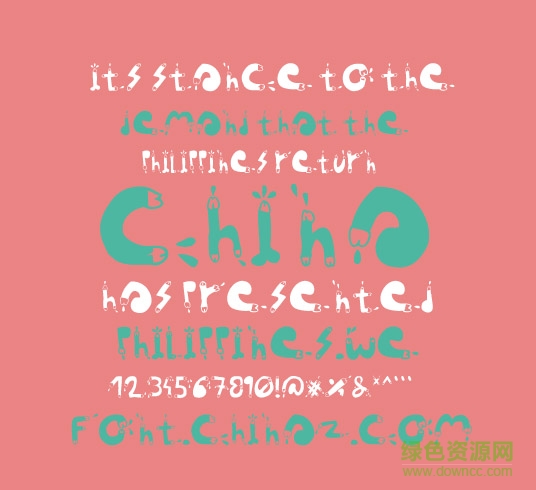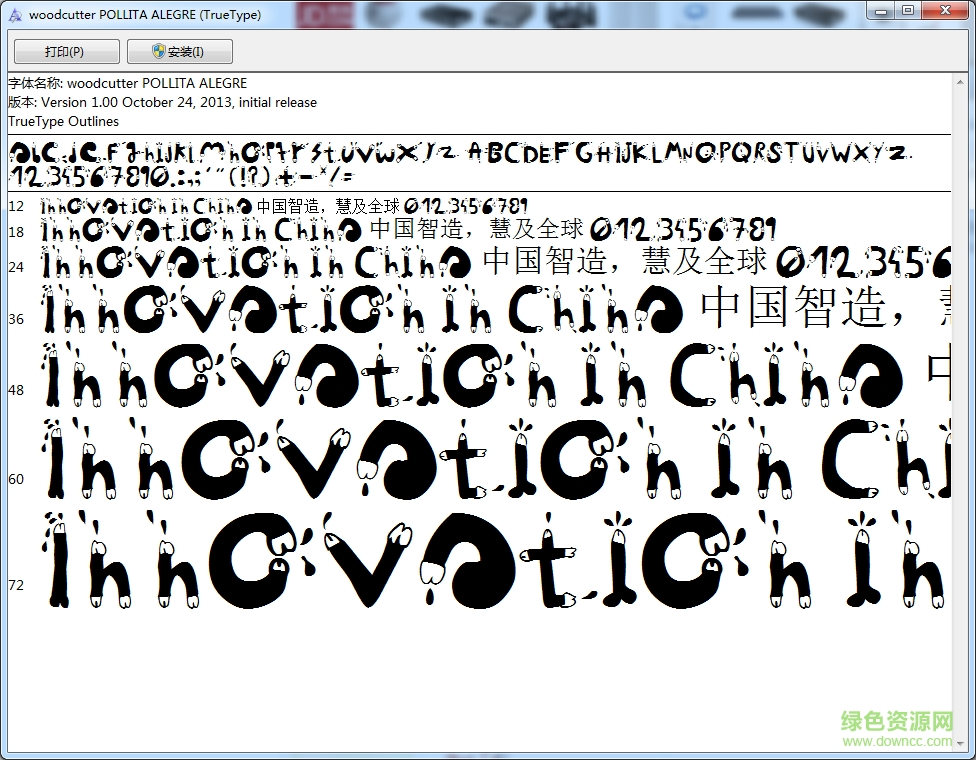
woodcutter字體
woodcutter字體是一款非??蓯矍纹さ淖煮w軟件,字體粗細(xì)均勻,極具美感支持多種方式輸入顯示,在線安裝即可使用,時(shí)刻彰顯個(gè)性特色??靵砭G色資源網(wǎng)下載體驗(yàn)吧!
woodcutter字體介紹
woodcutter字體是一款風(fēng)格非常鮮明的英文字體,它具有端正、橫豎整齊的特點(diǎn),字體又有一點(diǎn)分叉的小心機(jī)設(shè)計(jì),非常時(shí)尚。
woodcutter字體